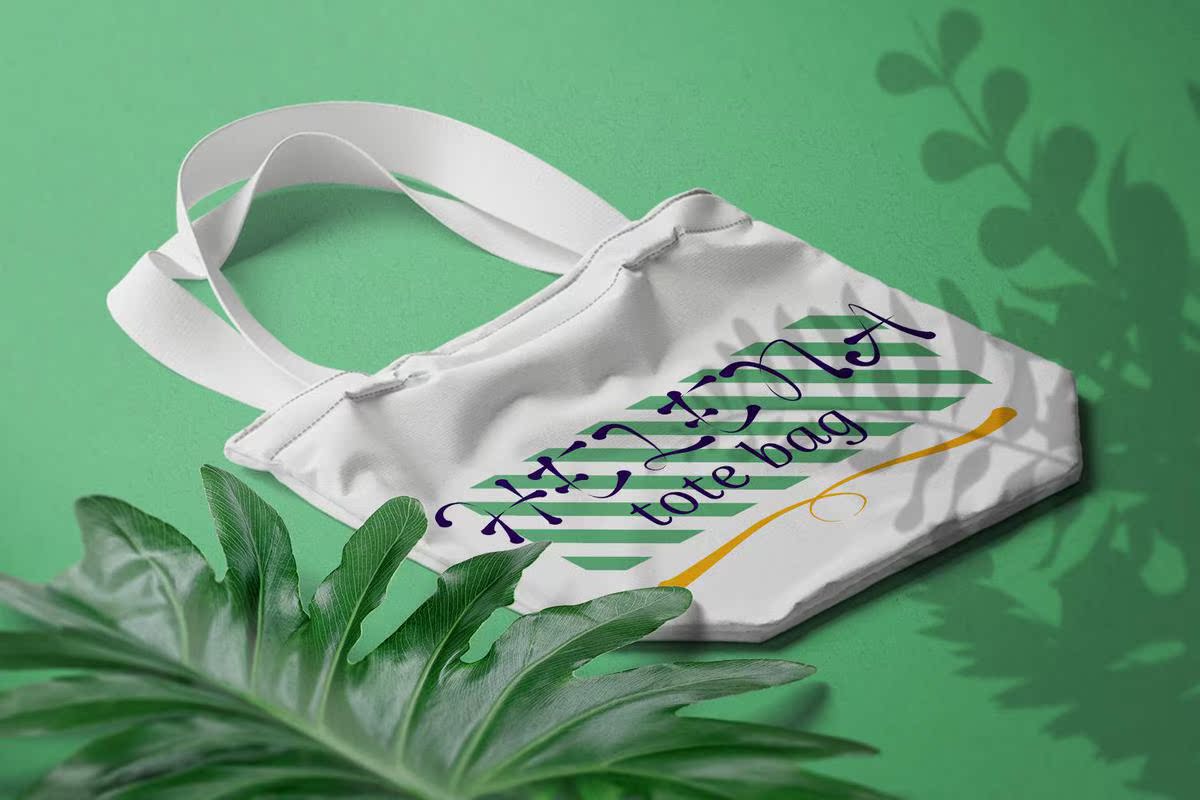
Aladyne是HizartDesign设计公司的一款现代书写字体。它是一款精美的Weetd设计,能让您的设计具有优雅的个性。Aladyne在徽标、贺卡、包装设计、耐磨性、工艺设计、任何项目、书名、婚礼宣传、包装等方面都是完美的,还有更多。Aladyne是HizartDesign的现代字体。它是一款精美的Weetd设计,可以让您的设计具有优雅的个性。Aladyne在徽标、问候卡、包装设计、耐磨性、工艺设计、任何项目、书名、婚礼宣传、包装等方面都非常完美。